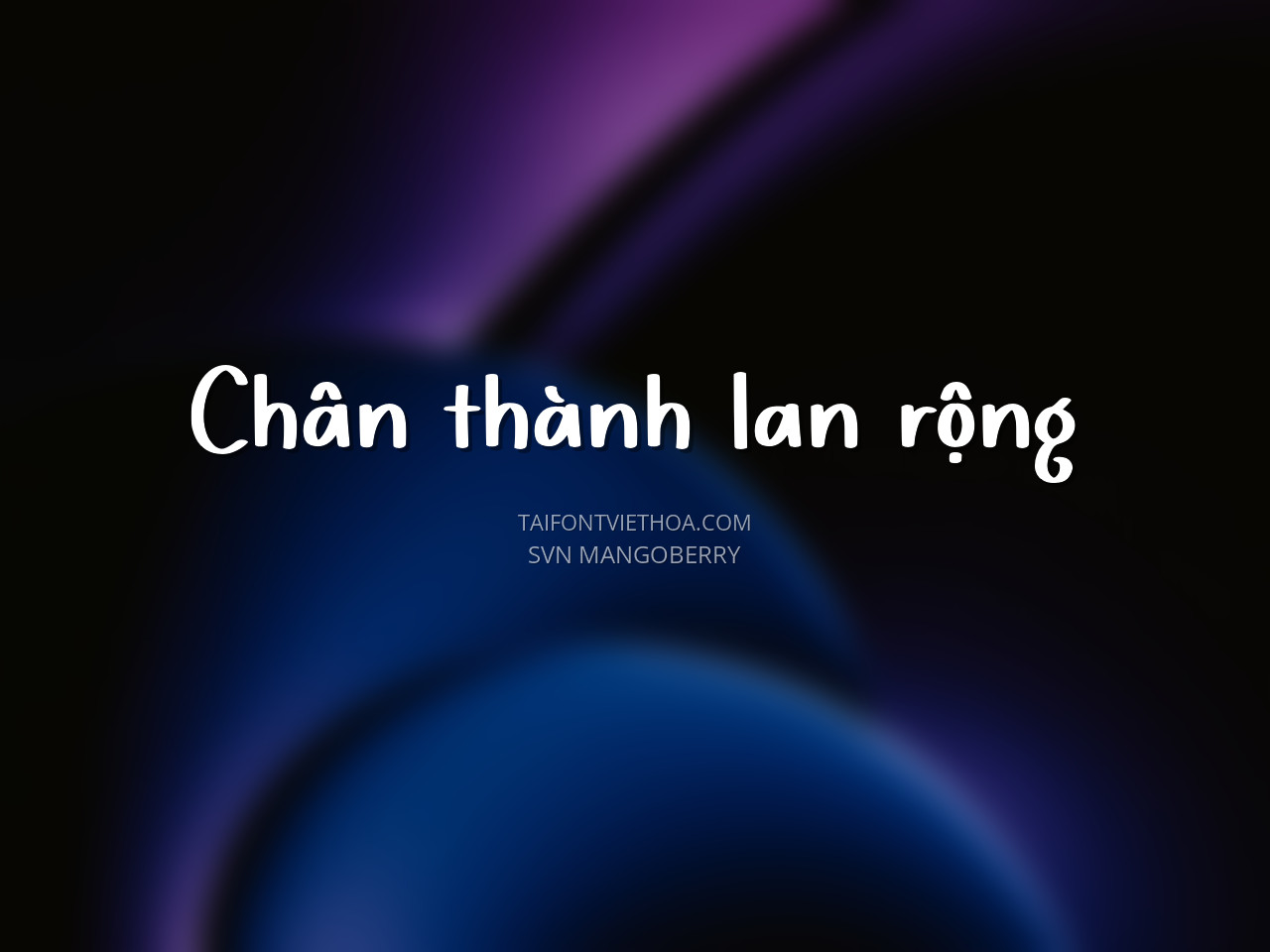
Font việt hóa SVN Mangoberry
Giới thiệu về font SVN Mangoberry – Kiểu chữ viết tay trẻ trung, tươi sáng và năng động
SVN Mangoberry là phiên bản Việt hóa của font Mangoberry – một kiểu chữ handwritten mang phong cách trẻ trung, năng động và đầy sức sống. Font được thiết kế với các nét chữ mềm mại, uyển chuyển và hơi nghiêng, tạo cảm giác vui tươi và thân thiện, rất phù hợp cho các dự án thiết kế sáng tạo, mạng xã hội và thương hiệu hướng đến giới trẻ.
Phiên bản Việt hóa của SVN Mangoberry được Taifontviethoa.comlựa chọn kỹ lưỡng, hỗ trợ đầy đủ dấu tiếng Việt cùng hơn 60 ngôn ngữ khác. Font giữ nguyên nét năng động, tươi sáng của bản gốc, giúp các nhà thiết kế dễ dàng áp dụng trong nhiều sản phẩm đa dạng với phong cách trẻ trung và hiện đại.
Thiết kế viết tay mềm mại – Lý tưởng cho thương hiệu trẻ và truyền thông xã hội
SVN Mangoberry sở hữu các nét chữ mềm mại, liền mạch và cân đối với độ nghiêng vừa phải, tạo nên sự hài hòa và sinh động trong tổng thể thiết kế. Font mang lại cảm giác gần gũi, vui tươi và dễ đọc, phù hợp cho tiêu đề, lời chúc, bài đăng mạng xã hội hoặc các sản phẩm sáng tạo cần sự biểu cảm trẻ trung và tươi mới.
Ứng dụng lý tưởng: thiết kế bài đăng mạng xã hội, bao bì sản phẩm, thiệp mời, logo thương hiệu trẻ trung, poster sự kiện và các dự án sáng tạo cá nhân. Ngành nghề phù hợp: truyền thông, thời trang, mỹ phẩm, giải trí, giáo dục và các thương hiệu định vị theo phong cách năng động, trẻ trung.